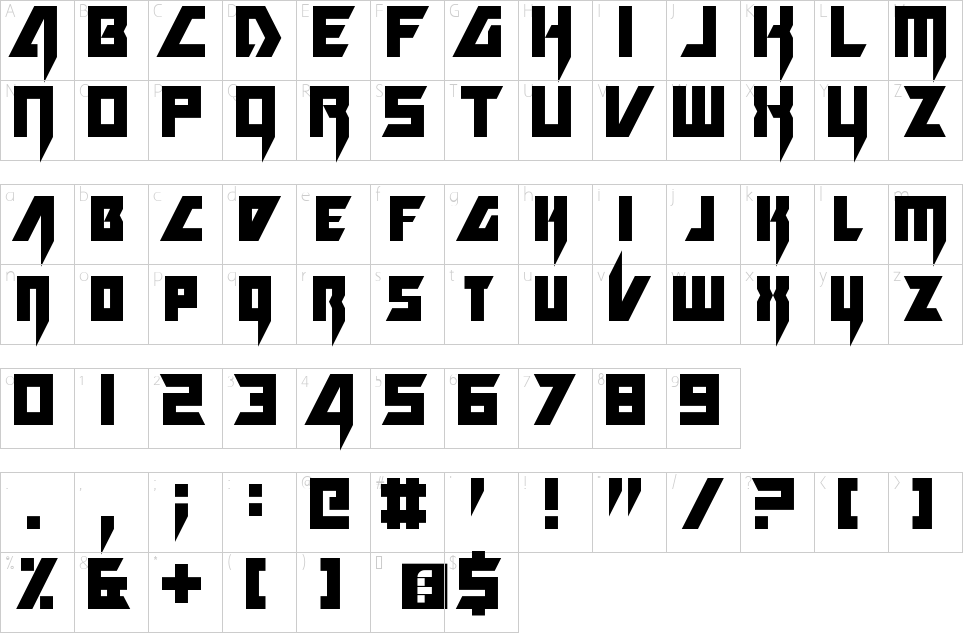
Death Hector Font
Aqui está uma descrição em português do Brasil para a página de download da fonte ‘Death Hector Font’, mantendo os requisitos fornecidos: A fonte Death Hector é um desenho moderno e elegante projetada pelo designer Chequered Ink, disponível tanto para Windows quanto para Mac. Esta opção gráfica única traz uma sensação fresca e contemporânea ao seu trabalho de design, com linhas definidas que se adaptam perfeitamente a textos longos ou estilos de escrita mais elaborados. Com mais de três mil visualizações desde sua disponibilização gratuita pela Chequered Ink, Death Hector é uma fonte versátil e moderna para qualquer projeto gráfico. Engaje seu público com o charme único desta fonte da categoria Grátis, que oferece um toque diferenciado sem precisar desembolsar grandes quantias.
Mapa de caracteres da fonte Death Hector Font